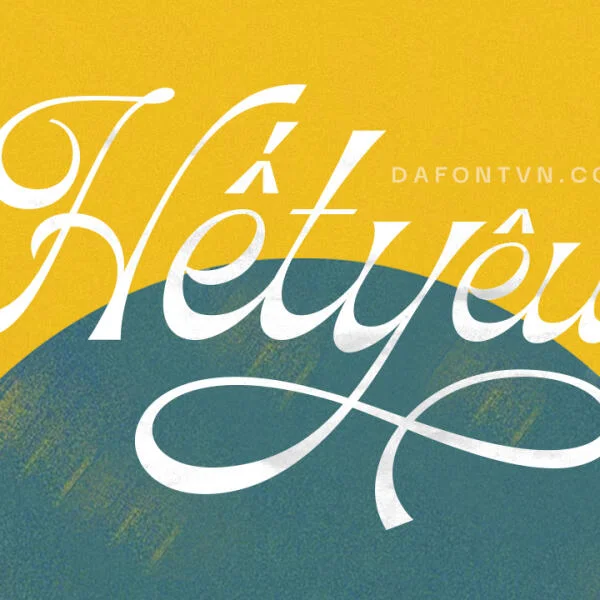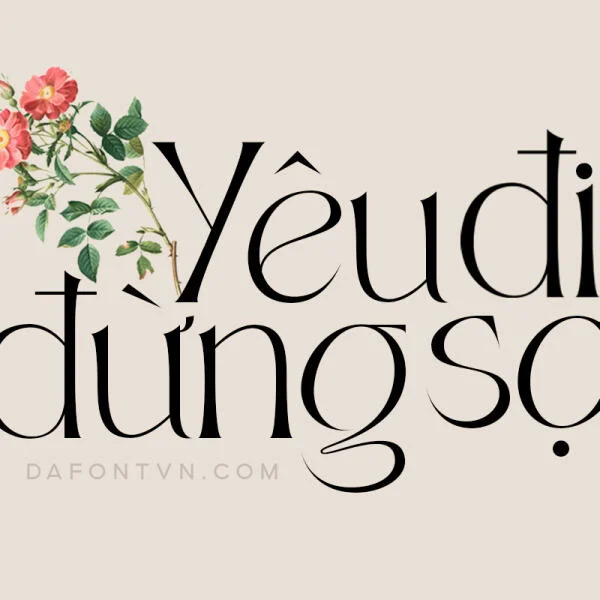
Tiệp tục chia sẻ tới bạn đọc một font chữ có chân cực đẹp - Font Fashion Hacks
Tổng quan về Font Fashion Hacks
Font Fashion Hacks - 1 kiểu font serif hiện đại lấy cảm hứng từ Art Nouveau (Tân thời đại) mang phong cách nghệ thuật đặc biệt là nghệ thuật trang trí với một vẻ đẹp rất ấn tượng và thời thượng.
Nếu bạn đang tìm kiếm một kiểu font hiển thị ấn tượng thì Fashion Hacks là một font chữ bạn không thể bỏ qua, Fashion Hacks mang đến sự hài hòa về kiểu chữ đẹp mắt cho nhiều dự án thiết kế khác nhau, bao gồm logo, typography, thiết kế sản phẩm, bìa sách...
Font Fashion Hacks mang đến những ấn tượng riêng vì vậy bạn hãy thử thiết kế biến hóa theo ý tưởng của mình nhé. Font được việt hóa đầy đủ, chỉnh sửa, tối ưu cũng như kerning.
Chi tiết các ký tự của Fashion Hacks